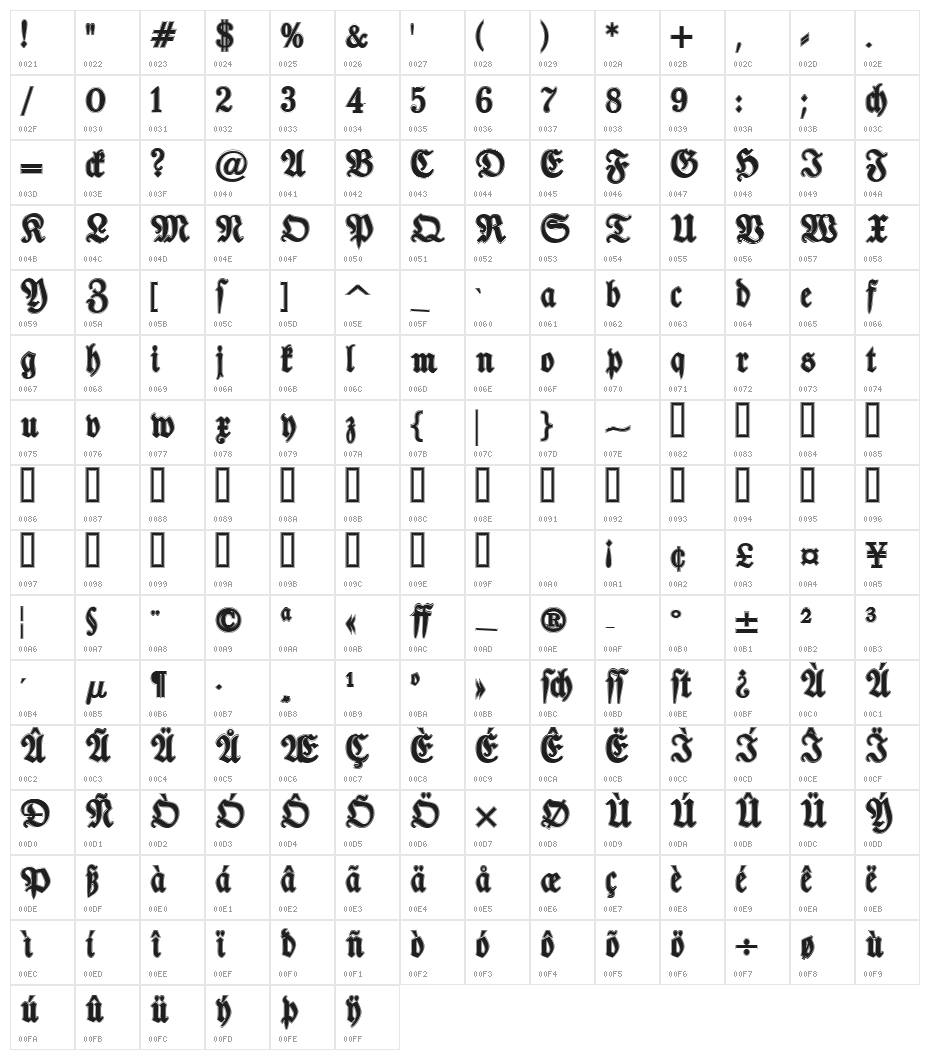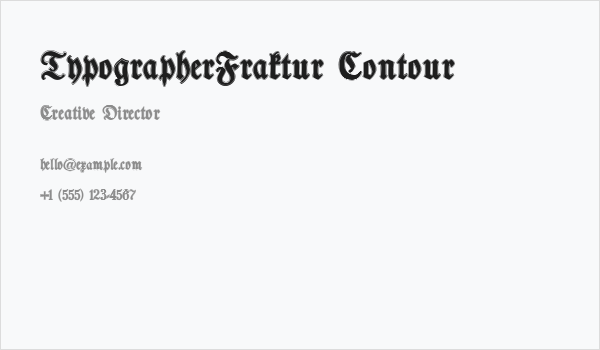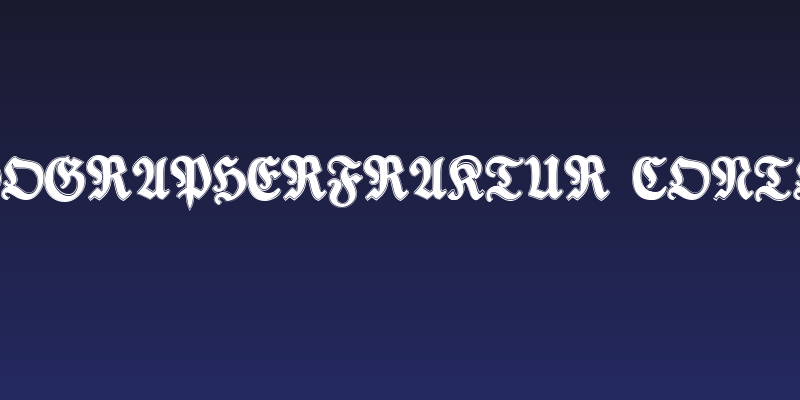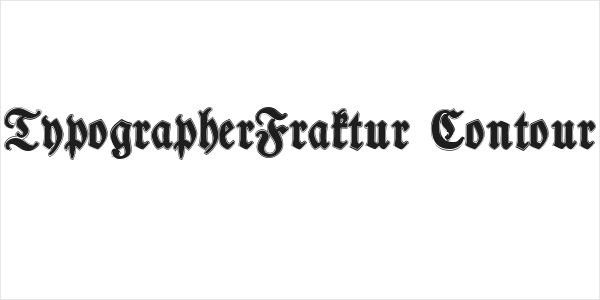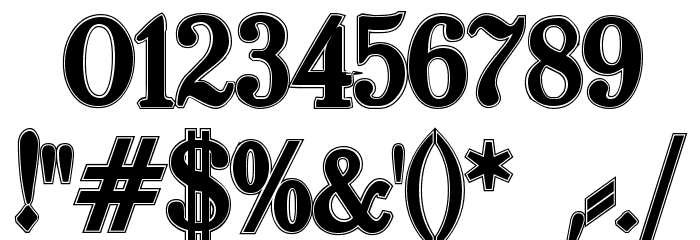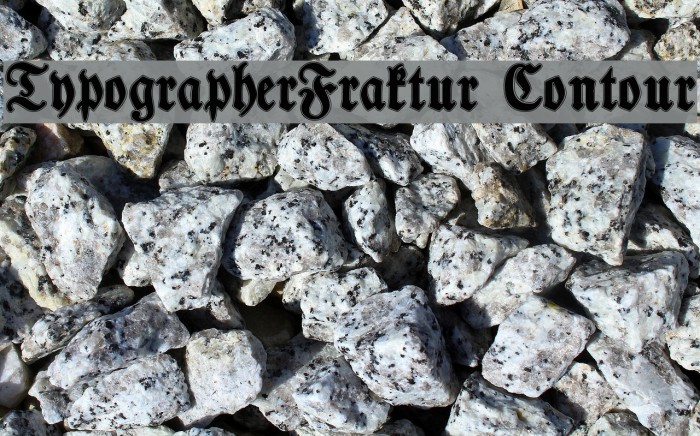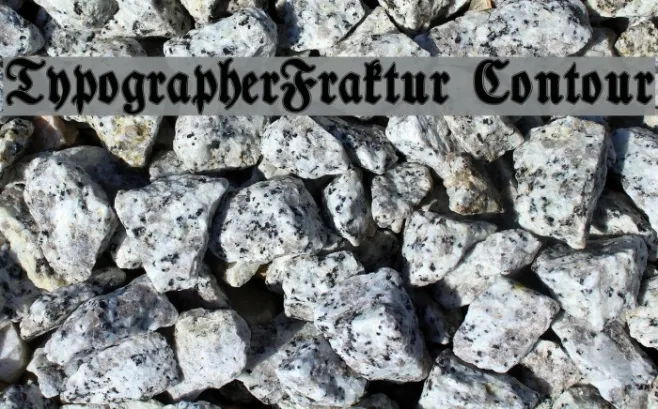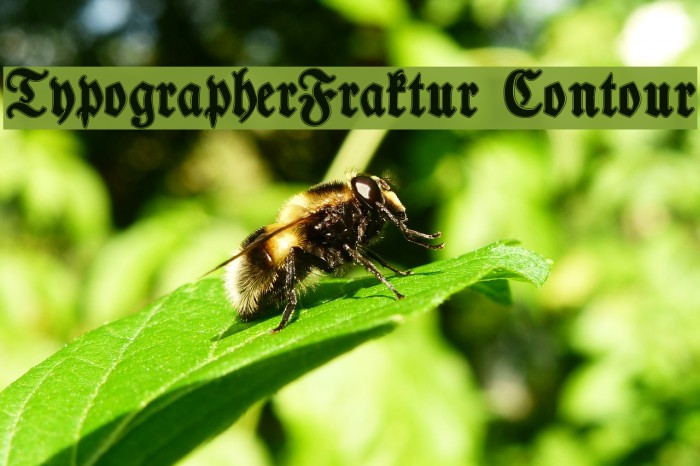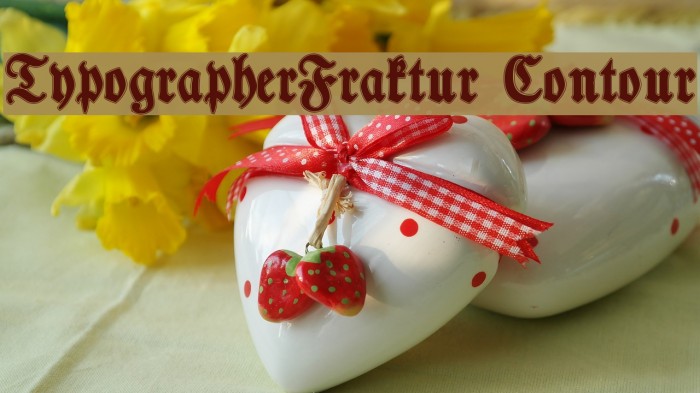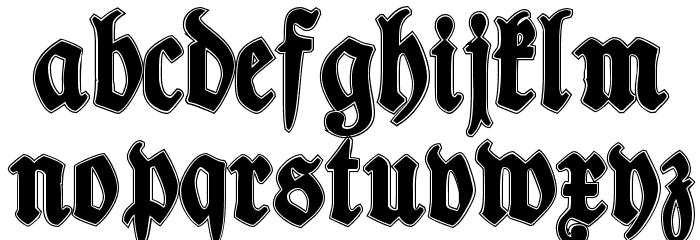
TypographerFraktur Contour Font
✎ Gothic
| Gesamtstil | Vintage, Gothic |
| Anwendungsfall | Logos, Headlines, Decorative purposes |
| Vorgeschlagene Projekte | Ideal for use in branding, logos, posters, book covers, and any project seeking a vintage or gothic aesthetic. |